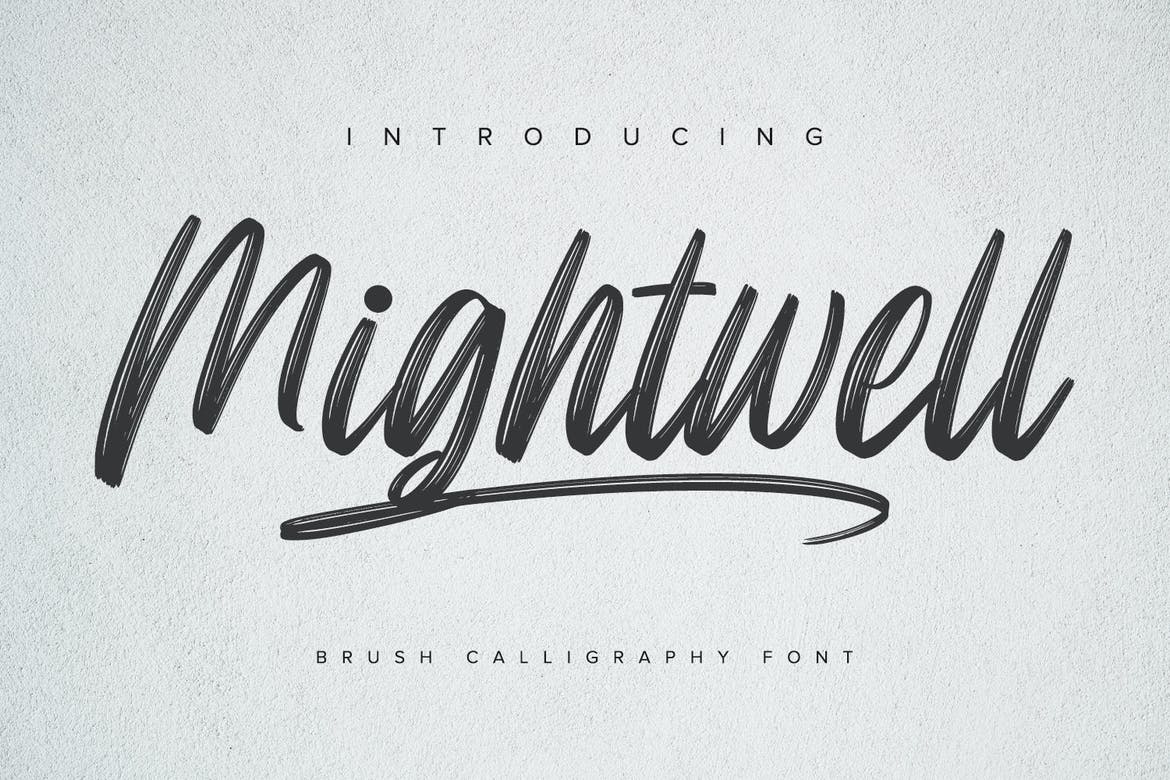
Mightwell es una fuente Brush moderna. Con un estilo manuscrito elegante y natural, trae un tipo de letra elegante y elegante. Mightwell se utiliza mejor para bodas, marcas, logotipos y citas.
- Hermosas Ligaduras
- PUA codificado
- Soporte multilingüe
- Números y puntuación